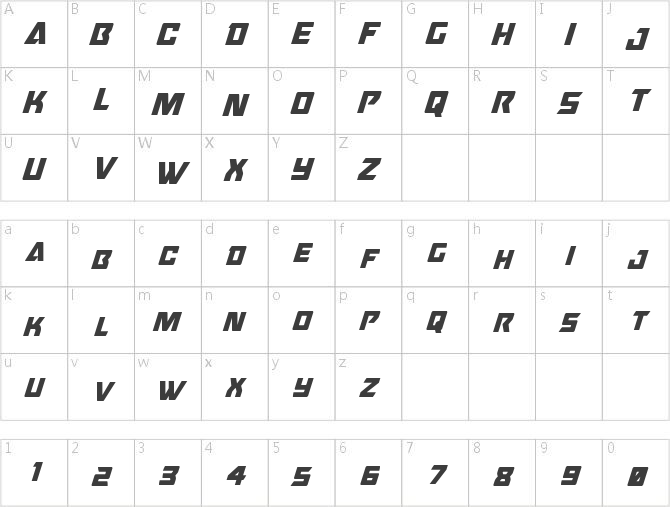
Oceanic Drift Condensed Italic
Oceanic Drift Condensed Italic介绍
Oceanic Drift Condensed Italic字体字库是一款让人赏心悦目、百看不厌的英文字体,适合各类广告和产品包装设计应用,字体大小0.03MB,格式为ttf字体,上传用户是舒甜咖啡,作者/版权方为未知